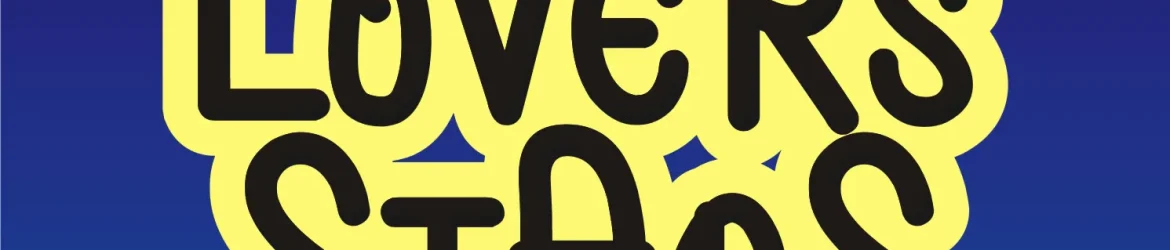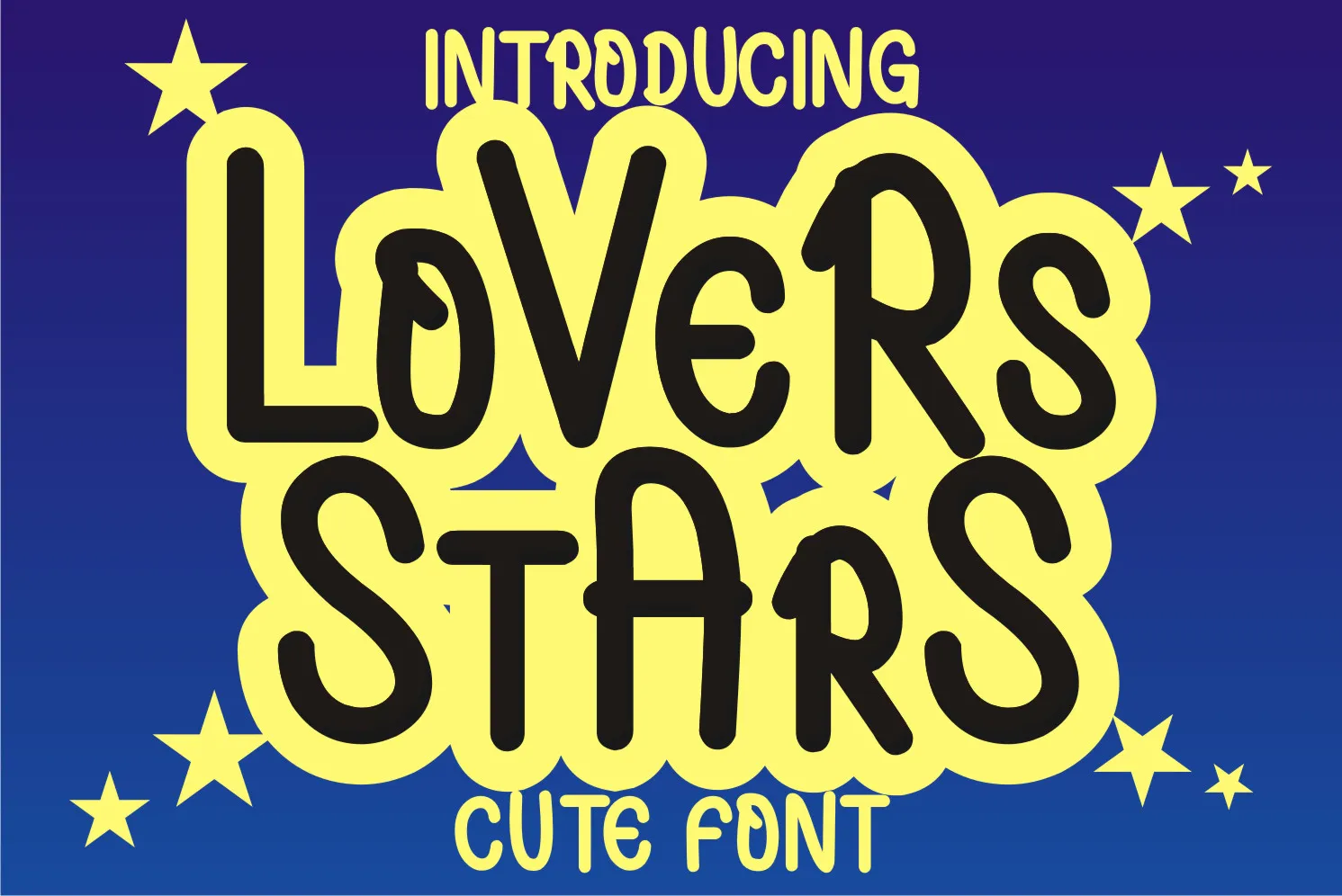
Lovers Stars Font – Fonte Grátis
Lovers Stars Font
Esta é uma fonte exibição cool e neat, cuidadosamente elaborada num estilo estiloso. Ideal para títulos de livros, revistas, posters, filmes, jogos, logotipos, marcas digitais e muito mais! Esta fonte atinge o ponto certo entre modernidade e elegância, garantindo um toque único em qualquer projeto visual que escolha aplicar. Seja para uma capa de livro intrigante ou a logo perfeito para seu novo jogo, essa fonte é um must-have na sua arsenal de recursos gráficos. Se você está buscando algo diferenciado e de alta qualidade, pode não haver melhor opção do que esta linda fonte ‘Lovers Stars Font’.